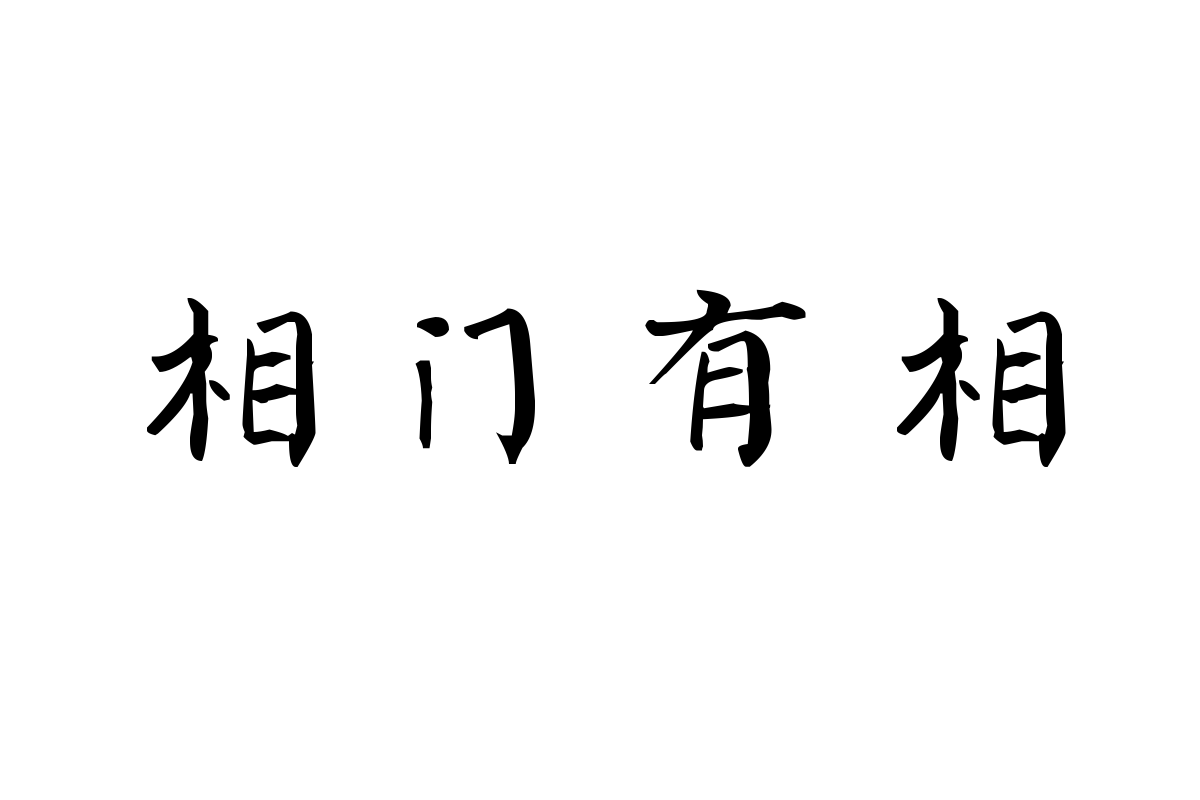
汉呈王天喜楷书是一种书法字体,由王天喜所创。这种字体的特点是笔画流畅、结构严谨、风格古朴。它的字形结构严谨,笔画粗细适中,线条流畅自然,给人以优美的视觉享受。
王天喜是当代著名的书法家,他的书法作品深受广大书法爱好者的喜爱。汉呈王天喜楷书作为他的一种创新尝试,将传统的楷书与现代的审美观念相结合,形成了独特的艺术风格。
这种字体在设计上注重线条的流畅性,通过调整笔画的粗细和间距,使整个字体呈现出一种和谐、平衡的美感。同时,王天喜在创作过程中也注重对细节的处理,使得字体更加精致、细腻。
总的来说,汉呈王天喜楷书是一种具有独特魅力的书法字体,它不仅展现了王天喜深厚的书法功底,也体现了他对传统书法的尊重和创新精神。